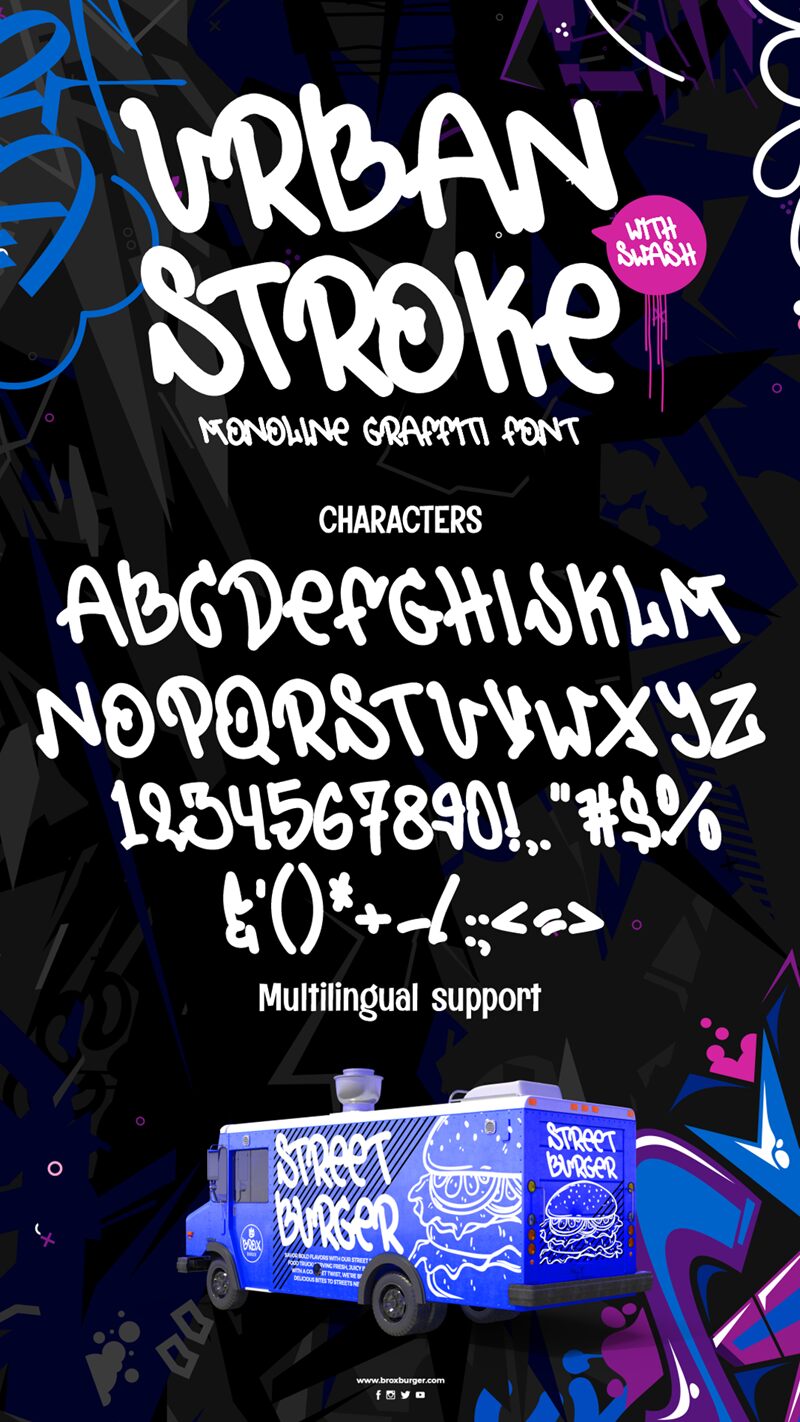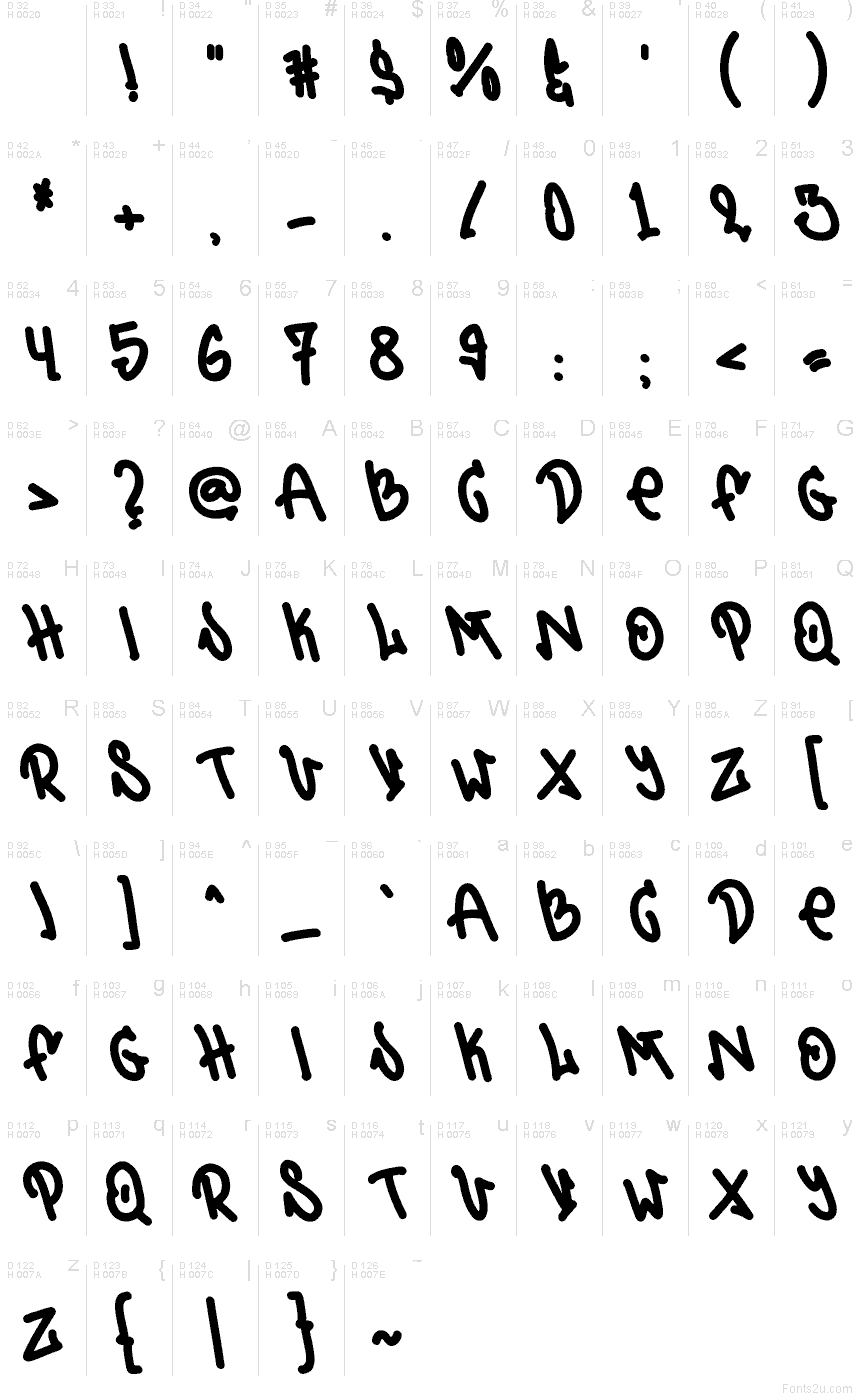
Urban Stroke, písmo od Muhammada Panji Ramdhaniego ze studia Sipanji x Figuree, působí jako čerstvý tah fixou na bílé zdi: tlusté, živé tahy s efektem mokrého inkoustu, díky kterým každé slovo doslova ožívá. Písmena působí rukodělně a trochu drzým dojmem, mají zaoblené konce a nepravidelný rytmus, který je výrazný, ale přitom přehledný.
Tento bezplatný graffiti font Urban Stroke skvěle vynikne na logách streetwear značek, v propagaci skateboardingu a tenisek, na hudebních plakátech, v náhledech na YouTube, na obalech alb, v sadách samolepek i v úderných nadpisech na sociálních sítích. Dopřejte mu prostor a zvětšete ho tak, aby štětcová textura zůstala ostrá; k datům, popiskům nebo detailům produktu ho kombinujte s čistým, zúženým bezpatkovým písmem, aby si hlavní sdělení zachovalo svůj švih.